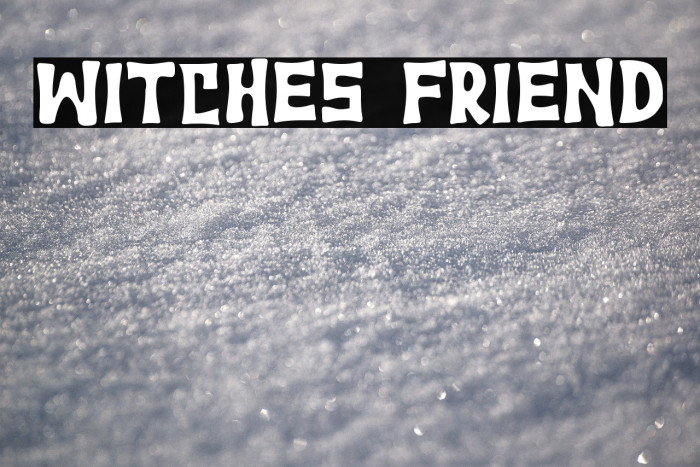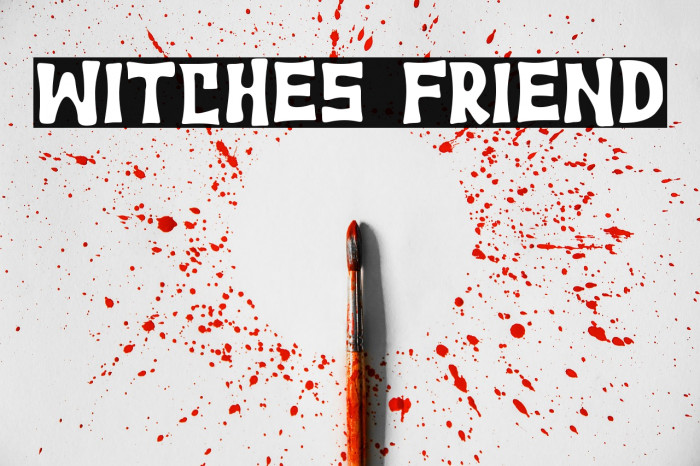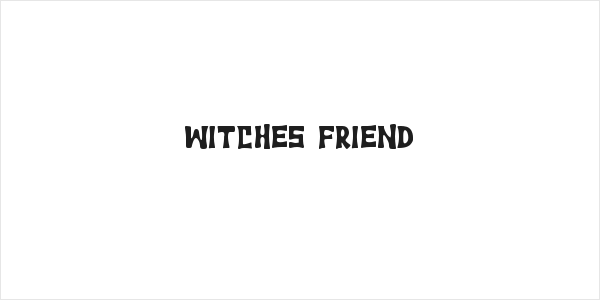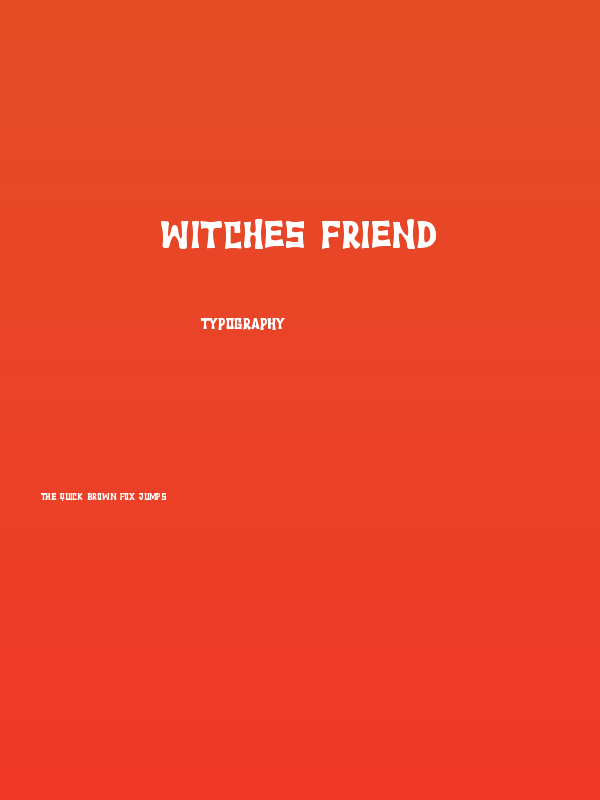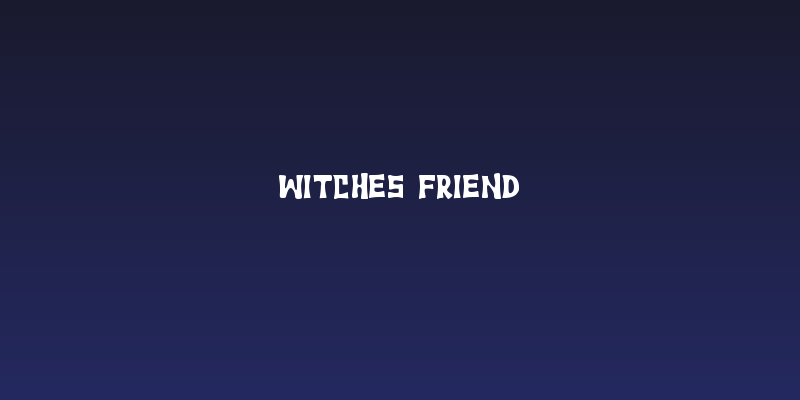
Witches Friend Font
| Stile generale | Whimsical, Playful, Fantasy |
| Caso d'uso | Headlines, Posters, Invitations |
| Progetti proposti | Ideal for Halloween-themed designs, fantasy book covers, children's party invitations, or any project needing a magical touch. |